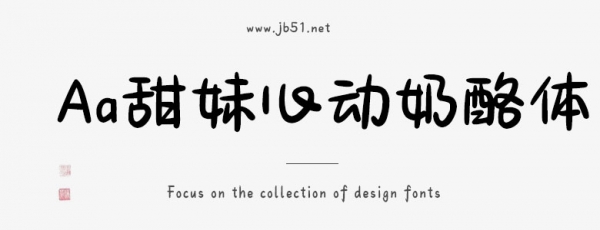
Aa甜妹心動(dòng)奶酪體由Aa字庫(kù)出品的藝術(shù)字體,字體筆觸適中,字形圓潤(rùn),具有很好的視覺(jué)感,適合應(yīng)用于藝術(shù)設(shè)計(jì)、平面宣傳設(shè)計(jì)、網(wǎng)頁(yè)設(shè)計(jì),書(shū)法字帖等領(lǐng)域。有需要的朋友快來(lái)本站下載使用吧。